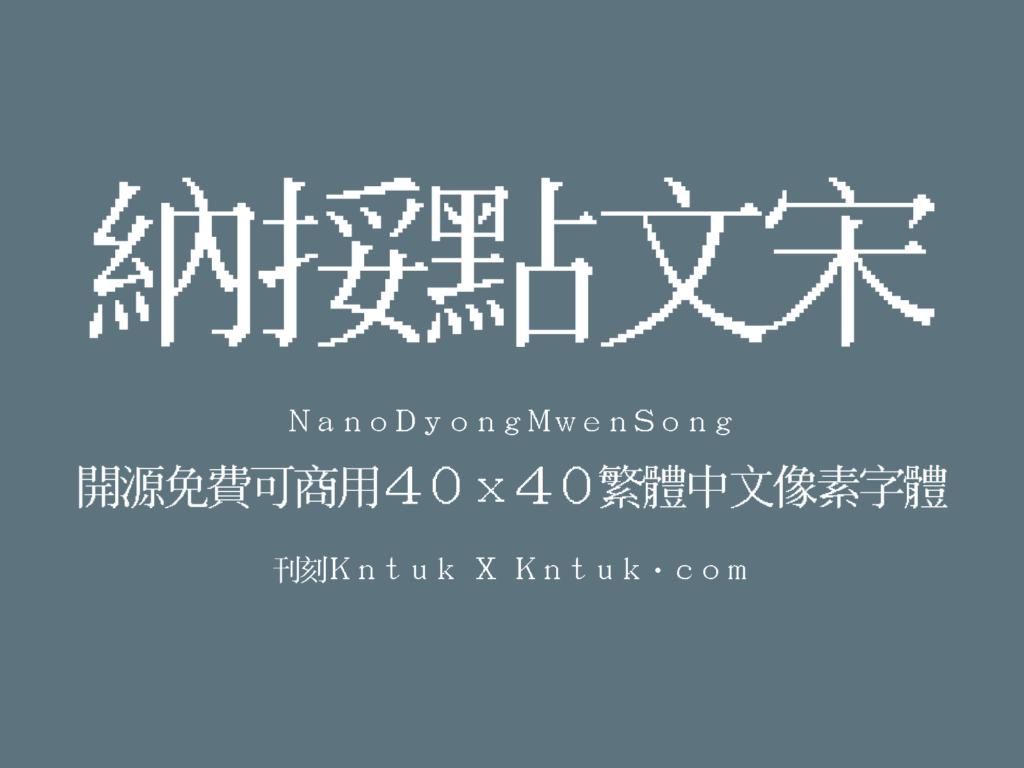
纳挼点文宋/納挼點文宋/NanoDyongMwenSong
一款40×40像素的超大字符集像素字体
纳挼点文宋/納挼點文宋这款字体最初是参照早年CNS11643标准的点阵字形进行复刻的,其实大家常用的纳米全大宋v1.0底层也是拿同一套素材做的。我拿到源文件后,重新整理了字符映射表并做了完整的编码转换,最终组合成了现在的版本。在兼容性方面,它除了能顺畅运行BIG-5这套繁体码表外,也把CNS11643的编码范围全部打通了,一至七区的所有文字都能被正确读取,处理跨字库或古籍排版时自然就不会遇到缺字的情况。